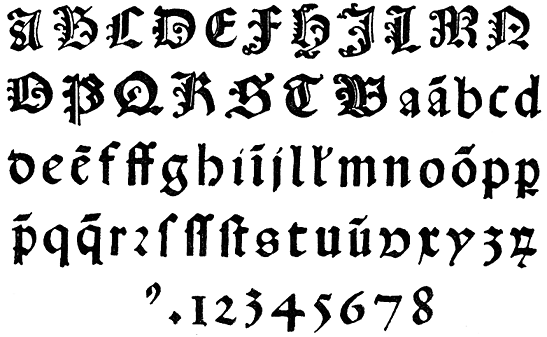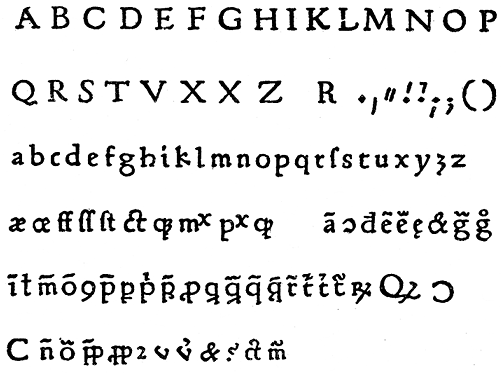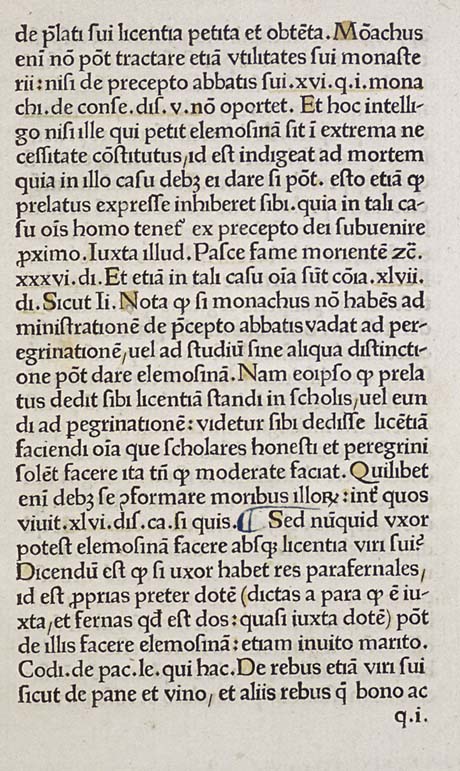
Ulrich Gering, prototipógrafoA imprensa foi introduzida em França em 1470 quando Johann Heynlin e Guillaume Fichet convidaram três impressores alemães (Ulrich Gering, Martin Crantz e Michael Friburger) para virem imprimir a Paris.Em 1470 foi instalada em Paris, perto da Universidade da Sorbonne, a primeira oficina de tipografia francesa. Os primeiros livros editados na Sorbonne vieram do prelo de Ulrich Gering, que foi aconselhado por Fichet e Heynlin em 1470-1472. Até 1477, Gering, Crantz e Friburger tinham imprimido cerca de 50 títulos de incunábulos. A partir de 1477, Gering continuou a imprimir por conta própria, associando-se por vezes a G. Maynyal, B. Rembolt e a outros. Imprimiu um total de 100 incunábulos.
Nos tipos metálicos que Gering e os seus parceiros usaram, facilmente se vê a transição do padrão tipográfico gótico para a letra romana, preferida pelos humanistas.